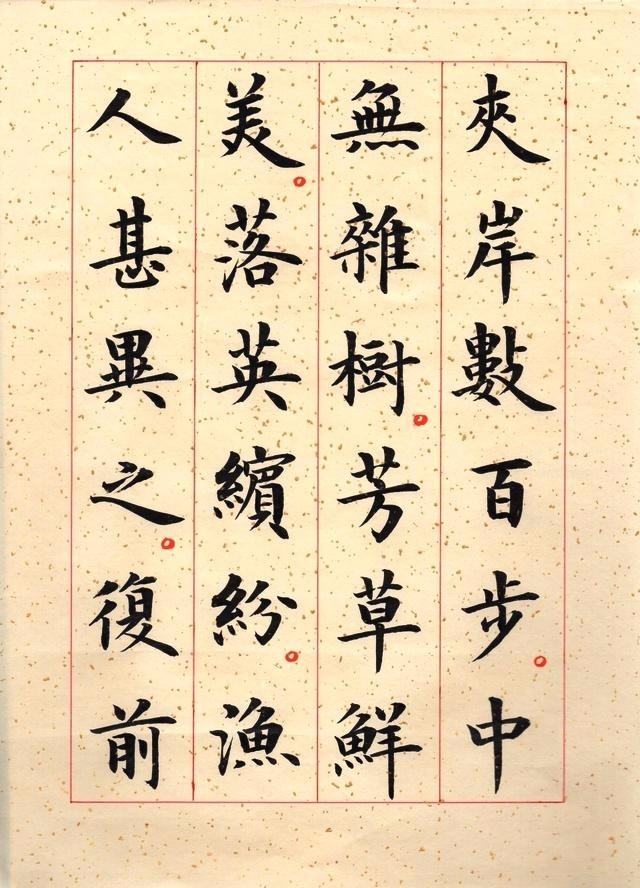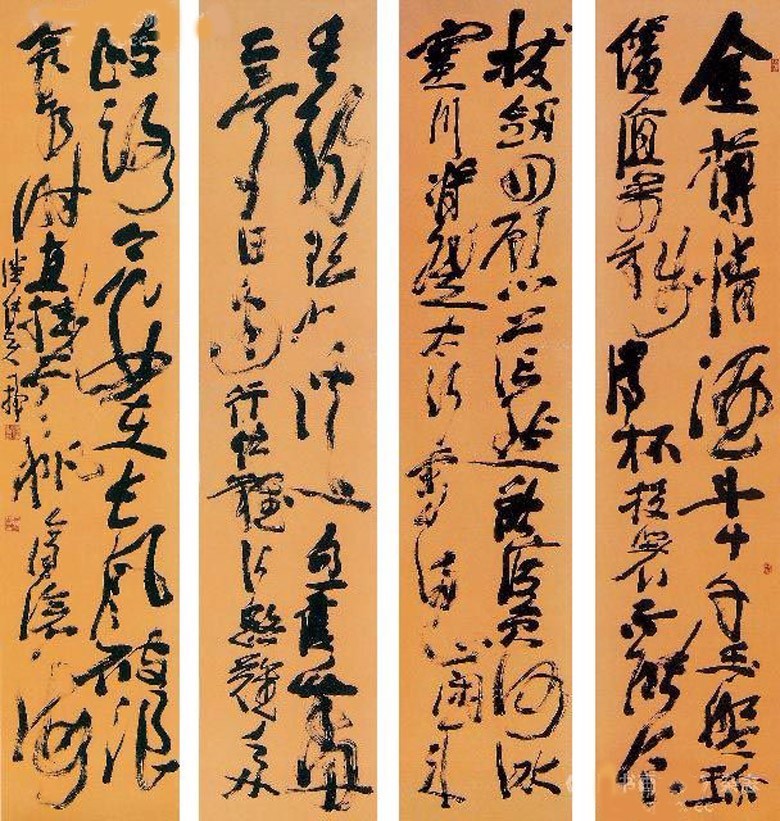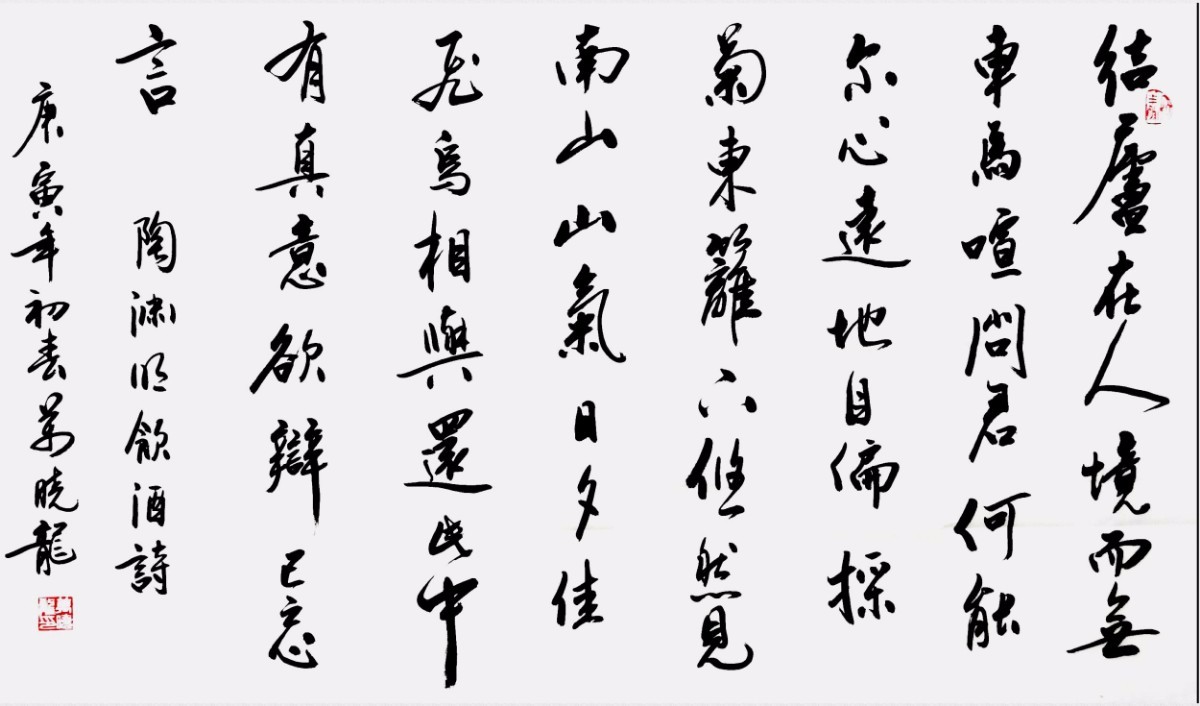
书法学习13个核心细节
1、书法学习需要时间的保证。虽然书法讲究悟性、天赋,这些先天的东西其实个人都差不了多少,最终还是落实到比耐心,比时间的投入上。耐心就是要做好长时间默默无闻的准备,深刻领会书法的精神,要对书法有感觉,或者说要“来电”。这个需要很多时间的投入,去不断的领会的。
2、学书法要深入传统,只有深入传统,真正领会了传统的精神,才会深切爱上书法。传统对于当代来说,不是枯涸的,它的资源仍然新鲜、活泼。对于传统的挖掘程度和理解的不同,可以开出不同的书法走向。
3、清代的碑学运动,传统的说法都认为在帖学系统之外建立了另外一个不同的审美世界。其实,碑学虽然讲究奇趣、古趣,他们的格调和品质仍然是在传统之中的,可以说仍然符合传统文人书法的审美的。我们看清末民初的碑学大家,如康有为、沈曾植、于右任等等,他们的书法突破了传统帖学,但是格调和品质仍然依归传统。我相信,书法同绘画一样,绘画强调所描绘对象的品格的塑造。比如说画松,就要具备松的品格。这个都是客观的对象所具有的基本品质。书法也是一样,我们写的汉字,每个字也都具有基本的品质,书法也是要把这种品质展现出来。而现代的一些学碑的书法家,认为奇趣就是变形,于是书法的取法对象走向民间化便成了众向所趋。这种对形式感的过分强调,其实是完全损害了书法的核心精神,即现代的书法丢掉了格调和品质。
4、书法的正脉乃是魏晋以来到明清书法名家构成的巨大的谱系,就是帖学系统,包括帖学的笔法以及帖学所崇尚的审美价值,即格调和品质。但是帖学在宋以后为什么衰弱了呢?具体原因有很多。其一:范本的差异性太大。刻帖的流行一方面扩大书法群体,而一方面也引起了诸多误会和混乱。刻帖的不断翻刻,离原本会越来越远,后人学刻帖,难免有雾里看花的遗憾。这个是资料的限制,而我们现在的信息时代,完全可以突破古人资料匮乏的尴尬局面,这个可以说是我们学书法的有利条件。其二:宋以后楷书的意识太强,可以说深刻影响了行草书的创作和审美。从唐代开始,中国的文字就在走规范化道路,这个大概和印刷术有关系。唐之前,文本的流传都是靠手工抄写来完成,对于每个阅读者来说,每一个文字都是新鲜的、不同的。但是在唐以后,印刷术的流行,带来了美术字在印刷行业的大量运用。美术字就是规范字,如宋体,虽然刻工的不同会让规范字有所差异,但是总体来说,规范字确立了一个标准的书体形式。对于阅读者来说,天天接触的就是这些一模一样的标准形式,这种规范字的阅读,深刻影响了书法家对于书法创作的理解。这些规范的字体会逐渐在阅读者的心里造成一种心理定势——字的某种写法就是完美的,字的笔画安排符合某种规范就是完美的,等等等等。而这些心理定势在魏晋人那里根本没有。魏晋时代的书法远绍汉代。汉代到魏晋这几百年中,成熟的书体不是楷书,而是草书。也就是说,魏晋人学书法,面对的是一个成熟的草书系统,而不是如宋以后,面对的是一个成熟的唐楷系统。这样差距就出来了。草书对于楷书来说,更加自由开放,从草书化到行书,行书必定具有草书的品格。所谓古法,就是一套从草书中化出来的笔法系统。而宋以后,学书先学楷书的做法成了书法的常识,也可以说是偏见。我们一开始就被灌输规范化的审美。这种审美的最终结果就是馆阁体的出现。明清的帖学笼罩在馆阁体的阴影之下,奄奄一息。帖学的最后一位大家就是明代的董其昌。但是,我们看到董的书法结构平正(正是楷书影响的结果),笔法单调。唯一出色的就是墨法和格调。而到了清代,更没有帖学大家。对于我们来说,困难也许更大。我们面对的是极其规范的阅读文字,同时离魏晋时代有千年的距离。这些都给我们领会古法造成了困难。
5、那么如何领会古法呢?最重要的是资料一定要丰富。这个可以说是我们的优势。比如说,学习唐楷,必须废除清代对唐楷的歪曲。我们可以参看日本流传下来的诸多书法作品。比如说日本空海和尚的作品中更多的保留了颜真卿的笔法;在嵯峨天皇的书迹中,我们看到了经典的欧阳询笔法,比欧书《千字文》要活泼的多、精彩的多。这些书迹对于我们理解唐人的笔法有着重要的意义。又比如说《兰亭序》,冯承素的摹本现在流传最广,大家对《兰亭序》的误解也最深。冯的摹本解体固然潇洒,但是毕竟是钩摹出来的,不是写出来的,露锋太多,显得尖刻和做作。有些笔画明显是违反运笔规律的,是假的笔画。学习《兰亭》如果不能认识到这一点,那就很麻烦。所以,从某种意义上说,禇遂良、虞世南的临本远比冯摹本和定武本重要。尤其是禇遂良的临本,值得好好研究。因为它是书写的结果,保留了更多唐人的笔法。虽然结构风神不如冯本潇洒,但是线条更真实。
6、学书法一定要占有丰富的资料,可以互相比勘。我们占据的资料多于古人,这个是我们时代的优势。但是,我们的资料更多的是印刷品,于是问题又来了。印刷品说到底还是二手资料,虽然比刻帖要好的多,但是对于理解古人书法还是存在着一定的差距。所以要看真迹,这个非常重要。多比勘资料,多观摩真迹,我们就能发现原来被我们深刻误解的东西。比如说《伯远帖》,我们看印刷品觉得非常精彩。但是上次我去上博参观的时候,发现《伯远帖》的线条居然这么软弱,这个让我很吃惊。
7、接下来讲书法学习问题。要学好书法需要全面的训练,最基本的就是技巧的训练和积累。技巧说到底就是练笔性。这个需要手的灵活性和控制笔锋的能力。所谓全面的技巧训练,就是要拓宽手的敏感度。书法经过历史的积累,技巧非常多。但是真正能被书法家吸收和运用的也不过十多种。但是对于学习者来说,要扩大技巧训练的范围,不要局限于几种技巧的训练。广泛的接触、涉猎,最终找到适合自己生理和心理的技巧。而真正丰富的技巧在二王的书法体系中得到最全面的保留。
8、五种书体各有各的技巧要求,或多或少。论技巧的变化、复杂和难度,行草的技巧要求更多,也更难。但这个不是说技法相对简单的篆、隶、楷不重要。相反,这些静态书法的研习对于我们掌握动态书法(行、草)有着重要的意义。林散之先生是当代草书大家,他成功的基础是隶书。老先生每天悬腕写隶书,慢悠悠的。这种对笔的控制力和稳定性的学习对他的草书影响巨大。而相反,我们看到现代的一些书家,专好写草书,线条打滑,留不住笔,明显是静态书法的功力不够。所以说,技巧的训练要全面。五种书体的学习可以同时展开。即把静态书法和动态书法的学习结合起来。学会每种书体用不同的状态书写。美院那边还有一种方法,同样的一个内容,用同一种书体,尝试用不同的状态来表达,这种训练难度更高,但也更有效。
9、技巧和人文。记得前几年,国美和南艺的书法教学有过争论。在国美一方,讲究完全解剖技巧,“逼真模仿”,这种精微训练见效快。而南艺讲究长远的修为,见效慢。当然,对于我们来说,完全可以结合两种学习的方法。首先,学习书法一定要学会运用理性剖析作品。国美的方法很适合。其次要对书法作品保持新鲜感。如果一件书法作品换不起你的感觉,一是作品肯定没有深度,二是你自己缺少深度。比如对于二王尺牍,需要经常产生新意,就是新鲜感,才能不断深入。王字可以说大有文章可做。最后,当技巧掌握到一定程度,必然要加强人文、品格等等方面的修养。
10、学书法对于整个书法史发展脉络要有清晰的把握。我们之所以说晋、唐是中国书法史上的两座高峰,就是因为书写在那个时候保持了最自由、最本真的状态。前面说过,印刷术带来的美术规范字对宋以后的书写产生了重大影响。在晋、唐时代,书法家的书写思维和现代人完全不一样。我们学传统,尤其是学宋以前的书法,就是要打破自己对文字的“意象”,就是说要突破深藏在自己潜意识中的规范的美术字审美定势。如果我们带着这种潜意识去欣赏晋、唐人的作品,会发现很多奇怪的地方,也就是说超出了我们想象之外。这些奇怪的地方对于古人来说是顺理成章的,对我们来说却是不可理解的。原因就是我们被固定的规范框住了。学习传统,尤其是学习宋以前的传统,说到底就是要打破原来的思路、规范(打破单一的美术字结构),如此才能真正理解古人。
11、“逼真临摹”非常重要,就是要达到伪造的地步。很多人以为临摹只要抓住大概,他们自称是书法的“气韵”、“神”等等。其实,所有的气韵神采都是建立在笔墨的基础上的。如果笔墨无法达到或者接近古人,大谈“遗形取神”等等都是空洞无物的。所以,在临摹的开始,要无条件的服从古人。要抓住古代作品中丰富多彩的差异性来临摹。比如说,对于一些奇异的结构,很多人会认为是偶然的效果,不必在意。其实这些偶然也透露了一种必然。我建议都要临,临的越像越好。也许一开始觉得很难,难就对了,那是因为我们日常的规矩、定势在作怪。我们总是想把古人的作品在临摹中套入自己的规范体系中。这样就麻烦了。你越是重复,规范就越牢固。到最后,临摹只是加深了自己的偏见,而没有突破。精细临摹古人作品就是要突破我们被美术字深刻影响的规范意识。
12、二王的书法体系笔墨要素更完善。从中可以学到非常多的东西。说二王是中国书法的源头,是有道理的。深刻理解了二王,再学其以后的东西,会有“一览众山小”的畅快感。
13、要掌握“八面出锋”的运笔方法,就是要加强用笔的丰富性、灵活性。切忌笔锋偏在一边,这样字容易薄;也要忌讳把笔当作刷子一样使用,那会让线条变得单调乏味。